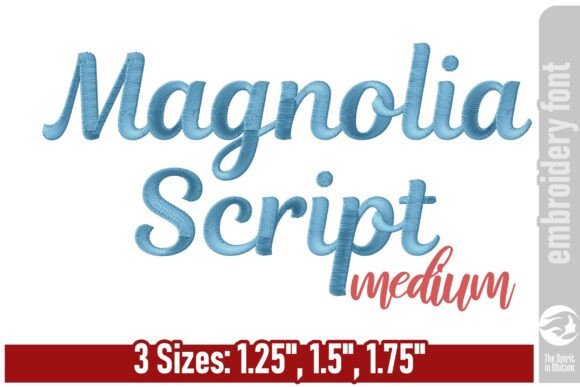
Magnolia Script Embroidery Font - Medium
การค้นหาองค์ประกอบการออกแบบที่เหมาะสมอาจเป็นเรื่องท้าทาย แต่ Magnolia Script Embroidery Font - Medium นำเสนอคอลเลกชันที่โดดเด่นซึ่งช่วยยกระดับงานของคุณได้ทันที
ไม่ว่าคุณจะสร้างผลิตภัณฑ์ POD (Print on Demand) คำเชิญงานแต่งงาน หรือกราฟิกโซเชียลมีเดีย Magnolia Script Embroidery Font - Medium ก็เหมาะสมอย่างยิ่ง